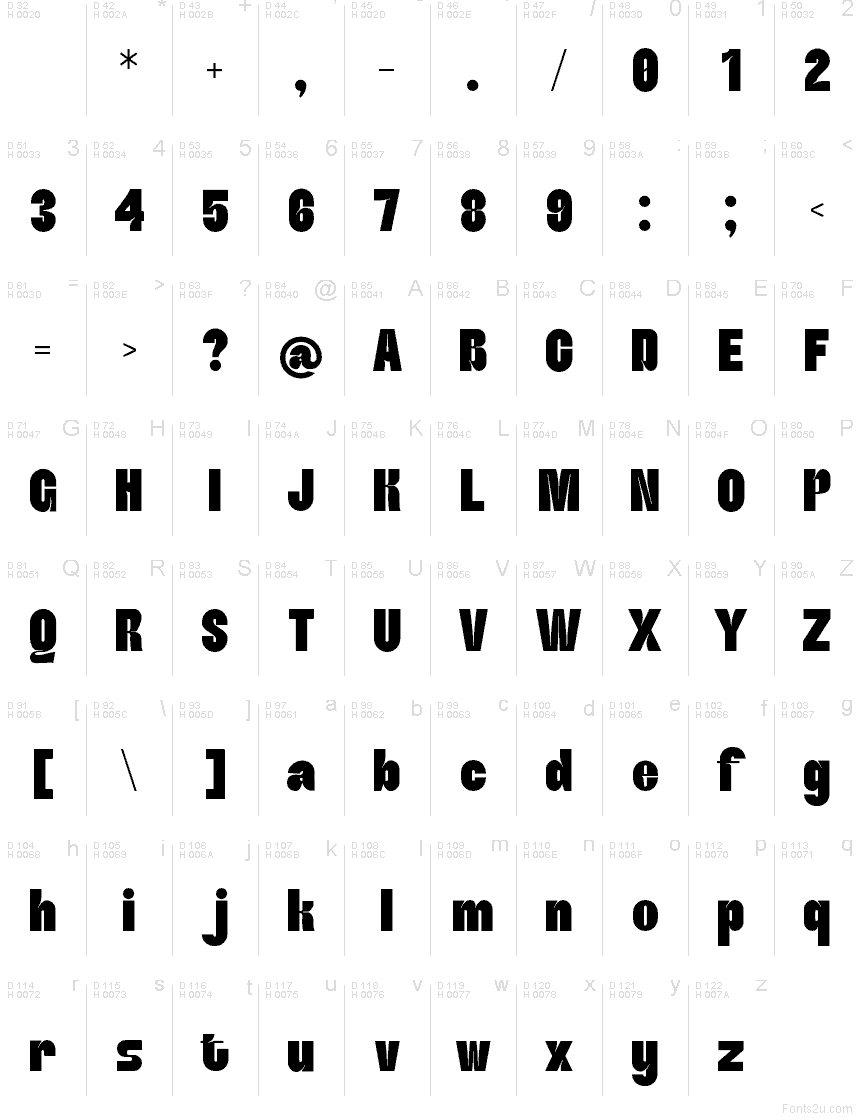
Monar, créée par Afkari Studio, est une police d'affichage moderne et gratuite, caractérisée par une silhouette lourde et sculptée. Ses lettres marient des masses larges et arrondies à des ouvertures verticales étroites et des découpes internes très effilées, créant un rythme élégant, presque digne d'un logo.
Cette police gratuite est idéale pour l'identité visuelle dans la mode, les visuels musicaux, les titres d'affiches, les couvertures éditoriales et les cartons de titres où quelques grands mots suffisent à structurer la composition. Ses formes denses et ses détails incisifs conviennent également aux monogrammes et aux logos typographiques empreints d'une tension contemporaine.